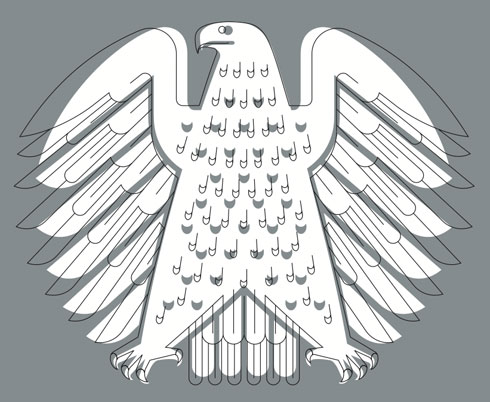
Die neue »Froh!« ist da. Leseprobe …
Froh! ist ein Gesellschaftsmagazin, das besondere Ereignisse des Jahres aufgreift und sich neugierig auf die Fragen und Themen hinter diesen Anlässen einlässt. Die Beitragenden schenken dem Magazin nicht nur ihre Texte und Bilder, sondern den Lesern auch neue, überraschende Blickwinkel. Die Winterausgabe ist ein eher stilles Heft geworden, eines für das man selbst still werden muss, um nichts zu überhören. Die Redaktion stellt Menschen vor, die genauer hingehört haben, zum Beispiel:
Martin Schleske, der schon beim Fällen eines Baumes hört, ob sich das Holz für den Bau einer Geige eignet;
Philip Gröning, der für seinen Dokumentarfilm „Die große Stille “ ein halbes Jahr in einem Kartäuser-Kloster verbracht hat;
Donata Wenders ist der Stille mit der Kamera gefolgt und
Christoph Schwyzer hat einen Ort gefunden, an dem die Zeit still steht.
PdW 51: Whomp, der Lettering-Zauberkasten
Immer Dienstags, das Produkt der Woche (PdW) bei FontShop, ausgesucht und preisreduziert. Heute: das OpenType-Scriptsystem Whomp, entworfen und programmiert von Alejandro Paul (Sudtipos), für 75 € statt 99 €.
Der amerikanische Schilder- und Werbemalers Alf R. Becker stand Pate bei der Entwicklung von Whomp. Seine Berufslaufbahn startete 1932 mit der Gestaltung einer Reihe von Alphabeten, die im christlichen Magazin »Signs of the Times« eingesetzt wurden. Im Durchschnitt entstand auf diese Art ein Entwurf pro Monat. Als Becker 100 solcher Schreibschriften ausgearbeitet hatte, veröffentlichte er diese in einem Buch, das Kult wurde unter den Schildermalern der USA. Doch erst in den späten 1990er seiner Entwürfe wiederentdeckt und teils digitalisiert.